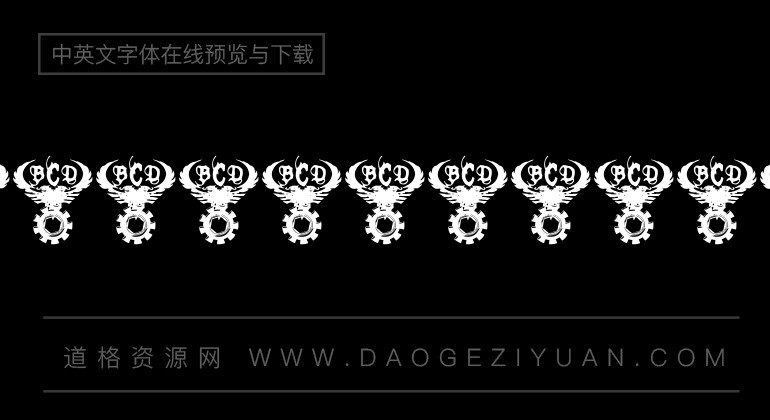
Prozac Buzz 字体是一种古怪的抽象字体,它的特点是把字母的表面细节抽象化,使用不规则的边缘和线条,营造出一种令人困惑的效果。Prozac Buzz 字体主要用于平面设计,可以用来创造抽象的标题或者标签,也可以用来制作海报和海报。它的外观非常有趣,可以提供一种独特的视觉体验,而且它的外观也非常现代,适合用来制作现代化的设计。内容介绍
Prozac Buzz是一款非常不错的手写艺术字体,具有很好的视觉感,适合于文化类的宣传设计、商业类品牌的广告和产品包装设计以及个性化文字排版等较多场景。